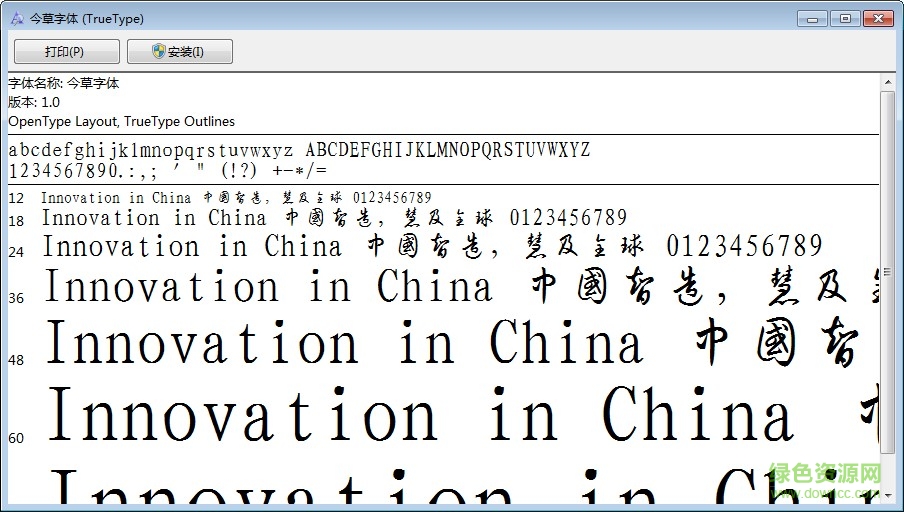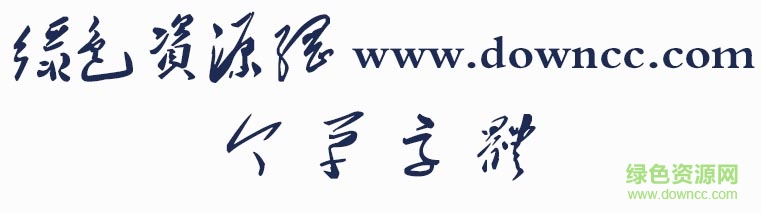
今草字體是一款免費(fèi)的草書(shū)字體,該字體創(chuàng)意獨(dú)特,字形簡(jiǎn)約灑脫,適用于創(chuàng)意字體設(shè)計(jì)或書(shū)法設(shè)計(jì)方面,感興趣的朋友歡迎在綠色資源網(wǎng)下載!
今草亦稱“小草”。草書(shū)的一種。始于漢末。是對(duì)章草的革新。筆畫(huà)連綿回繞,文字之間有聯(lián)綴,書(shū)寫(xiě)簡(jiǎn)約方便。為東晉王羲之所發(fā)揚(yáng)完善。唐代張懷瓘《書(shū)斷》載:“(王)獻(xiàn)之嘗對(duì)父云:古之章草,未能宏逸,頓異真體,合窮偽略之理,極草蹤之致,不若藁行之間,于往法固殊,大人宜改體。”更加縱放的“狂草”為“今草”的發(fā)展。